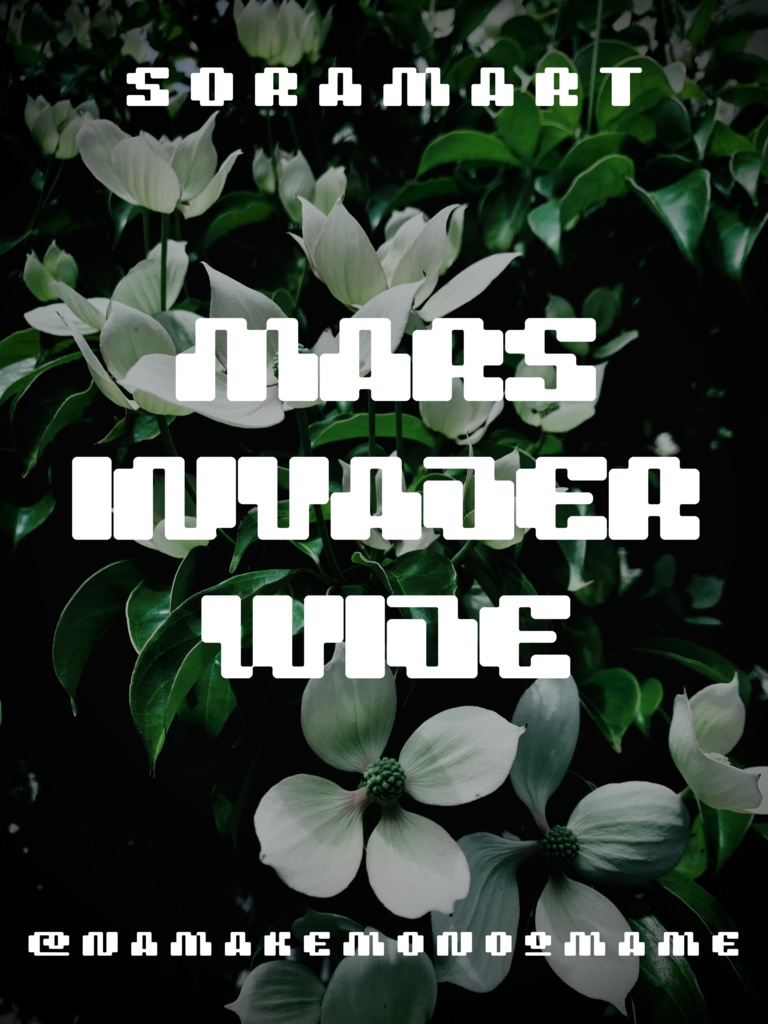
そらマートフォントデータ”Mars Invader Wide”Digital2,500 JPY카트에 담기기프트 보내기About Giftレトロフューチャーなゲーミング・ポップフォントの幅広アレンジ版"Mars Invader Wide" です。 「TrueTypeフォントファイル」という形式です。 ダウンロードした後、Zipファイル内のデータをインストールしてお使いください。 このフォントは商用利用可となっております。 お客様の制作・創作活動のお役に立てれば幸いです。 ※使用上の注意事項などは、添付のReadmeをお読みください。そらマートVisit FANBOX!Fontsフォントデータ”Dot Eat Bug Acid”そらマート200 JPYFontsフォントデータ”Dot Eat Bug Mild”そらマート0 JPYFontsフォントデータ”Dot Eat Bug”そらマート0 JPYFontsフォントデータ”Solid Voltage Strike”そらマート200 JPYFontsフォントデータ”Solid Voltage”そらマート0 JPYFontsフォントデータ”Henge Edge Rock”そらマート2,500 JPYFontsフォントデータ”Henge Edge Tall”そらマート0 JPYFontsフォントデータ”Henge Edge”そらマート0 JPYFontsフォントデータ”Chisel Stroke Wide”そらマート2,500 JPYFontsフォントデータ”Chisel Stroke”そらマート2,500 JPYFontsフォントデータ”Crushed Can Serif Empty”そらマート2,500 JPYFontsフォントデータ”Crushed Can Serif Wide”そらマート2,500 JPYFontsフォントデータ”Crushed Can Serif”そらマート2,500 JPYFontsフォントデータ”Dolce Cube Tall”そらマート2,500 JPYFontsフォントデータ”Dolce Cube”そらマート2,500 JPYFontsフォントデータ”Eight-bit Quest Wide”そらマート2,500 JPYFontsフォントデータ”Eight-bit Quest”そらマート2,500 JPYFontsフォントデータ”Tonik Crate”そらマート2,500 JPYFontsフォントデータ”Vapor Sprout Edge”そらマート2,500 JPYFontsフォントデータ”Vapor Sprout Wide”そらマート2,500 JPY더보기